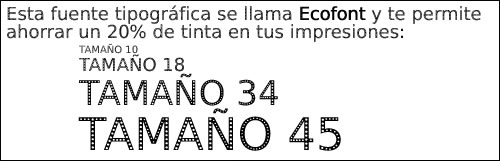
Ya que la tinta de impresora es uno de los líquidos más caros del mundo estaría bien poder gastar la mínima en nuestras impresiones ¿no? Pues es posible con Ecofont, una fuente tipográfica que permite ahorrar hasta un 20% de tinta gracias a su agujereado.
Aunque es una muy buena iniciativa, no tiene un diseño atractivo para escritos largos